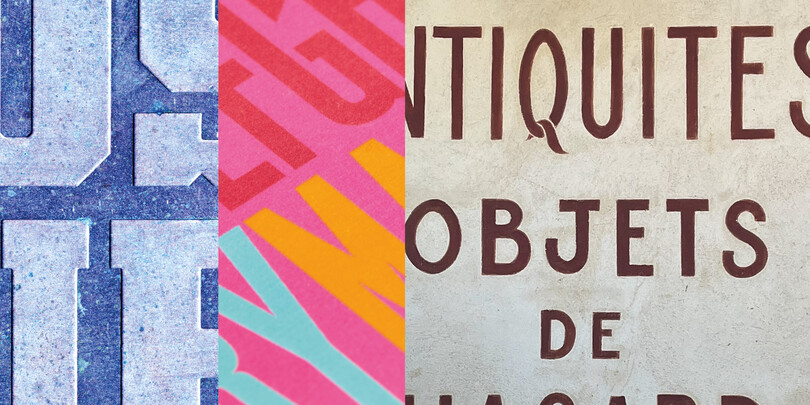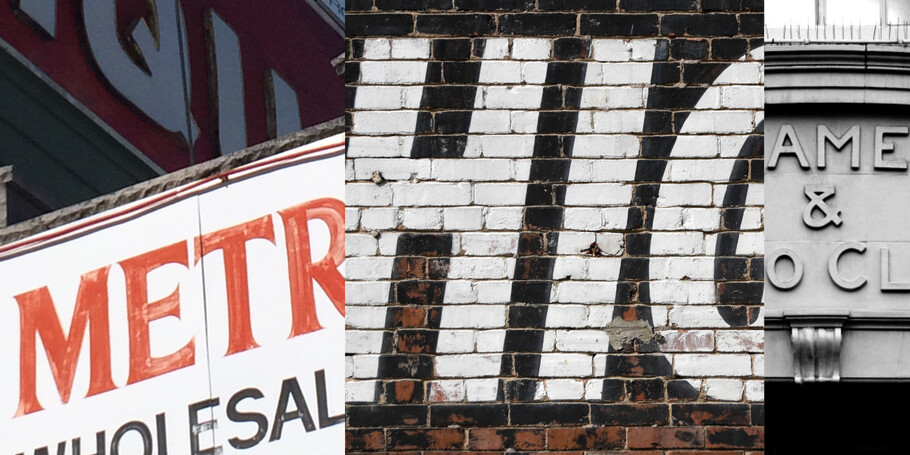
Ocho fuentes de inspiración infalibles para diseñar.
« Veamos cómo encontrar la inspiración para dar comienzo al flujo creativo y definir el tono del proyecto »
Los y las profesionales de la creación moderna pueden dejarse llevar, casi sin darse cuenta, por las tendencias y las últimas novedades. No obstante, es importante examinar las limitaciones asociadas al encargo en el que se está trabajando antes de avanzar demasiado en el proceso de conceptualización. Lo primero es lo primero: ¿cómo encontramos la inspiración para dar comienzo al flujo creativo y definir el tono del proyecto?
A continuación, te recomendamos algunos recursos que pueden servirte de inspiración y ayudarte en el proceso de diseño (porque seguramente ya hayas estado navegando por Behance y Pinterest):
1. The Brand Identity e It’s Nice That: ambos portales son recursos de diseño de alcance mundial y tienen por objetivo fomentar la creatividad (basta con echar un vistazo a la misión de It’s Nice That) con contenidos de alta calidad y muestras espectaculares de diseño gráfico y trabajo creativo.
2. Pangram Paper: el estudio tipográfico Pangram de Montreal (Canadá) desarrolla una plataforma editorial «experimental» con contenidos muy variados, desde noticias del mundo del diseño y lanzamientos de tipos de letras hasta entrevistas a profesionales del sector.
3. Newsletter de Fresh Fonts: se trata de una newsletter indie de pago que resume toda la actualidad del sector tipográfico. ¿Y sabes qué es lo mejor? A los suscriptores y suscriptoras se les envía una familia de fuentes gratis cada mes. Si te suscribes, estarás apoyando a profesionales independientes del diseño de tipos y, a cambio, recibirás en tu bandeja de entrada fuentes cuidadosamente seleccionadas.
4. Adobe Live: cada semana, Adobe organiza sesiones con profesionales de la creación que se emiten en directo a través de Behance. Estas sesiones se celebran en Francia, Alemania, el Reino Unido y Estados Unidos, y son un recurso increíble, ya que en ellas se profundiza en los perfiles de profesionales de la creación y se comparten sugerencias sobre diferentes aspectos de las prácticas creativas.
5. Pódcast Weekly Typographic: en este pódcast semanal organizado por la League of Moveable Type, que va por la tercera temporada, se habla en profundidad sobre la tipografía y la comunidad de diseño, lo que incluye exposiciones, nuevos lanzamientos y entrevistas con diseñadores y diseñadoras.
6. Instagram: es probable que ya uses esta plataforma, conocida por ser como «LinkedIn para especialistas de la creación», para compartir y descubrir trabajos creativos. Sin embargo, puedes optimizar tu feed para sacarle todo el partido posible. Selecciona los resultados que aparecen en el feed para obtener inspiración y no dedicar incontables horas a mirar contenido. Es imprescindible que guardes lo que te gusta de forma que puedas volver a encontrarlo.
7. Libros: puedes tardar años en crear una biblioteca personal versátil, pero merece la pena hacerlo para esos momentos en los que necesitas parar un poco y sentarte con algo tangible entre las manos. Pocas cosas sustituyen la sensación de pasar las páginas impresas, una sensación que, junto al contexto histórico, se pierde en la búsqueda infinita de contenidos en Internet.
8. El «mundo real»: cuando realizas un trabajo creativo, puede ser fácil centrarte demasiado en lo que ves en pantalla, pero no debes perder de vista el mundo físico que te rodea. Lánzate a la búsqueda del tesoro que contienen los letreros escritos a mano, la espectacular flora campestre y las curvas de los coches. Una vez que hayas entrenado a tu cerebro para que filtre aquello que te resulta inspirador, se convertirá en un proceso natural que harás sin pensar.
Si buscas más inspiración, echa un vistazo a campañas recientes en las que se haya hecho un uso excelente de los tipos y la tecnología.
Renovación de marca de la Orquesta Sinfónica de San Francisco a cargo de COLLINS. El trabajo que la agencia COLLINS y la fundición de tipos suiza Dinamo Typefaces realizaron conjuntamente para la Orquesta Sinfónica de San Francisco demuestra lo poderosa que puede ser la tecnología de fuentes variables cuando se utiliza para realzar tanto la voz de marca como el contenido. Las formas de los tipos son llamativas, contemporáneas y, además, adaptativas y variables: cada carácter se transforma en respuesta al sonido de la música. Estas fuentes son la prueba de que la tecnología de fuente variable puede potenciar un concepto de diseño cargándolo de sentido.
Renovación de marca de M&M’s a cargo de JKR. Este año, gracias a la agencia JKR y a Monotype, la emblemática marca de chocolates se sometió a un cambio de imagen para modernizarse y centrarse en su nuevo propósito: contribuir a un mundo en el que todas las personas sientan que encajan. Como parte del proceso, la marca también renovó la estética y actualizó la personalidad de sus famosos personajes M&M’s. Además, adoptó un tono más inclusivo y acogedor, e incorporó un tipo de letra personalizada y llamativa, llamada All Together, para crear una familia amplia, cálida, divertida y cercana.
Tipo de letra personalizada para los Juegos Olímpicos de París 2024, a cargo de Joulie Soudanne, diseñadora de Elliott Amblard; Sylvain Boyer, director de arte de Royalties/Ecobranding; y Tina Payet. Este tipo de letra personalizada, diseñada para los Juegos Olímpicos de 2024, es una referencia a los últimos juegos de París, celebrados en 1924, hace casi 100 años. Sus formas curvas e inclinadas reflejan el estilo dominante del momento, el art déco, sinónimo de la elegancia francesa. Por último, el tipo personalizado mezcla con acierto el estilo contemporáneo y la fuente variable, diseñada específicamente para adaptarse a todos los entornos.